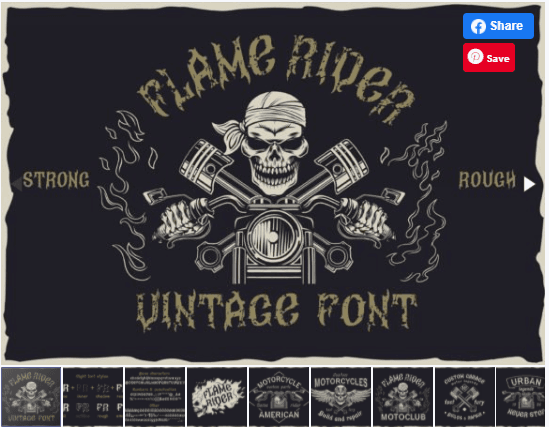
Flame Rider Font
Flame Rider - это крутой, жирный и напористый дисплейный шрифт. Этот шрифт, искусно разработанный для того, чтобы ваше творение выглядело не из этого мира, будет выглядеть внушительно и аккуратно в самых разных идеях, таких как брендинг, маркировка или логотипы.